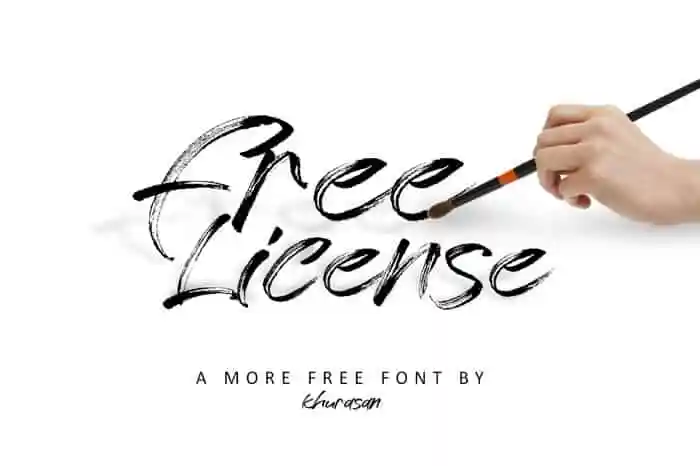
Free License Brush Font – Download Grátis
A Free License Brush Font é uma elegante escolha para designers que desejam adicionar um toque sofisticado a seus projetos. Inspirada no mundo das roupas luxuosas, essa font script minimalista apresenta ligaturas e alternativas de estilo, oferecendo um olhar único e vibrante às criações digitais. Ideal tanto para design gráfico quanto para elementos tipográficos em mídias sociais ou publicações online, a Free License Brush Font é perfeita para quem busca uma font que se destaca no mercado contemporâneo de design. Não apenas minimalista e elegante, ela também traz ligaturas sofisticadas e estilos alternativos prontos para dar um toque único à sua produção visual. Este é um excelente complemento para designers atentos às últimas tendências em fontes script, oferecendo uma opção de qualidade sem comprometer o seu orçamento.